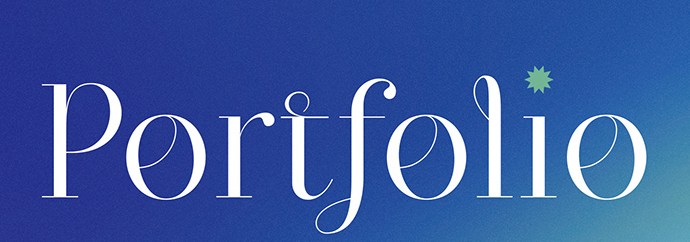
폰트찾습니다. hhh*** 2022.12.20 산돌폰트로 검색해봐도 안나오네요 무슨폰트인가요? 댓글 0 등록 진진 Shaping Heart Regular 이 폰트에 "i" 부분에 별모양만 커스텀 한 것 같습니다. 2022-12-20 답글 달기 hhh*** 감사합니다. 2022-12-22 답글 달기 댓글 더보기 쉽고 빠르게 가장 비슷한 폰트를 알고 싶다면? 이미지로 검색하기
Shaping Heart Regular 이 폰트에 "i" 부분에 별모양만 커스텀 한 것 같습니다.